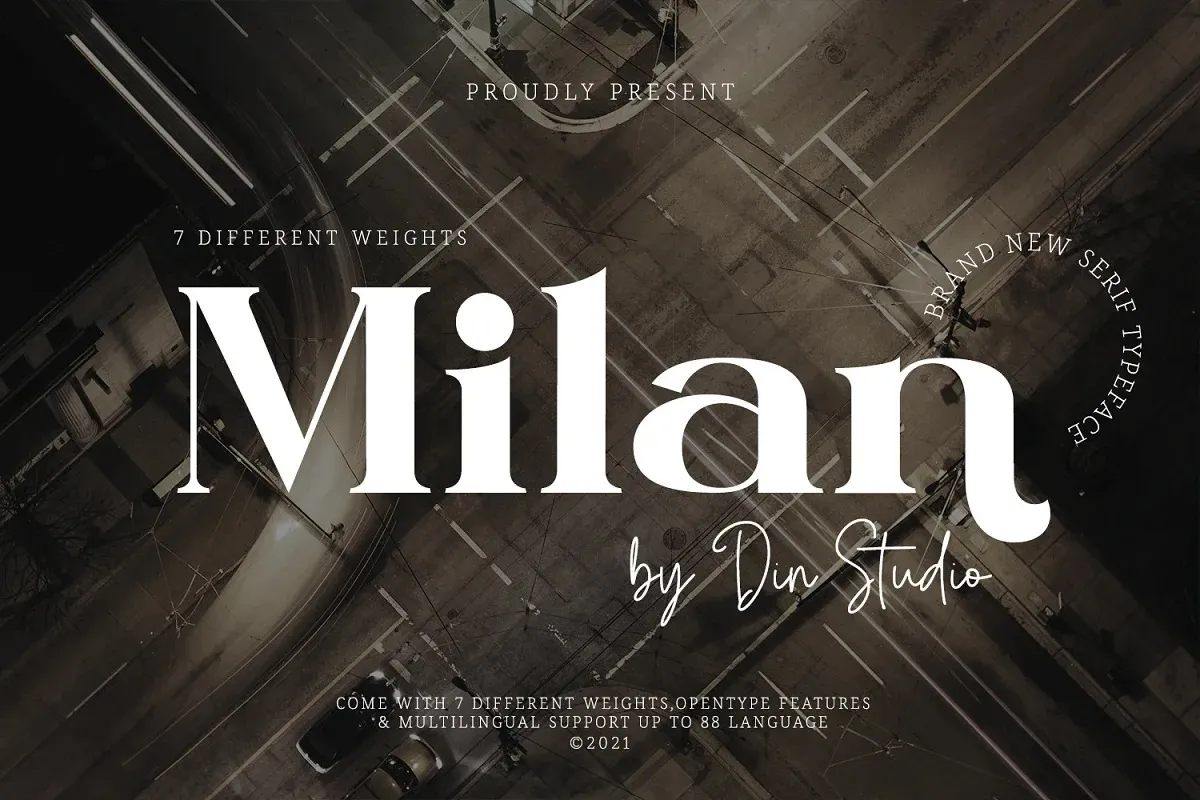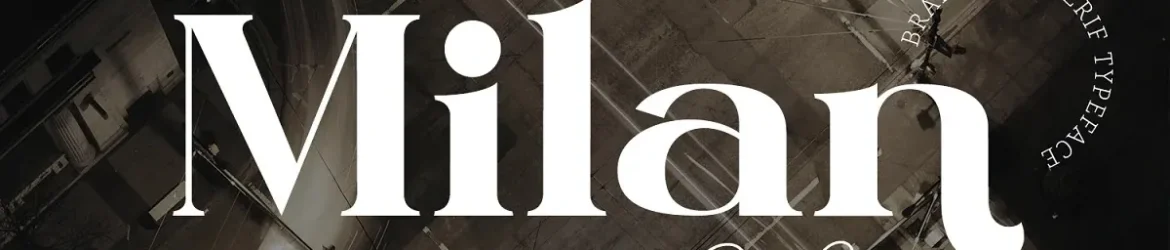
Milan Font – Download Grátis
Milan é uma elegante fonte serif com várias opções de peso para escolher. Se você busca estilo na sua tipografia, Milan tem a solução perfeita. Com este famoso conjunto, você terá muitas opções de peso para maximizar seus designs com fontes estilosas. O design da Milan é feito tanto em maiúsculas quanto minúsculas, o que torna qualquer leitura uma experiência agradável e suave ao mesmo tempo muito legível. Esta família de fonts é um excelente escolha para garantir um bom match de fonte para suas propostas criativas! Perfeito para criar marcas impressionantes, logotipos, menus, gráficos para mídias sociais e muito mais.